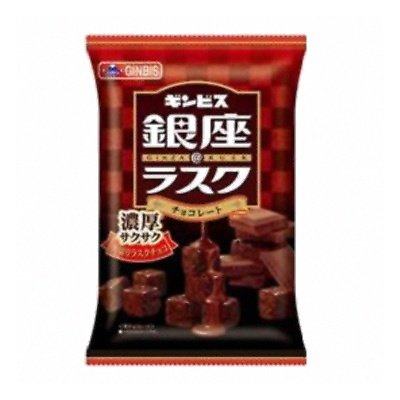
「銀座@ラスク」シリーズ
銀座@ラスクはとろける食感の新食感チョコラスクとして定期的に様々なフレーバーが発売されている。
銀座@ラスクのパッケージのタイトルにダイナフォントロマン鳳が採用
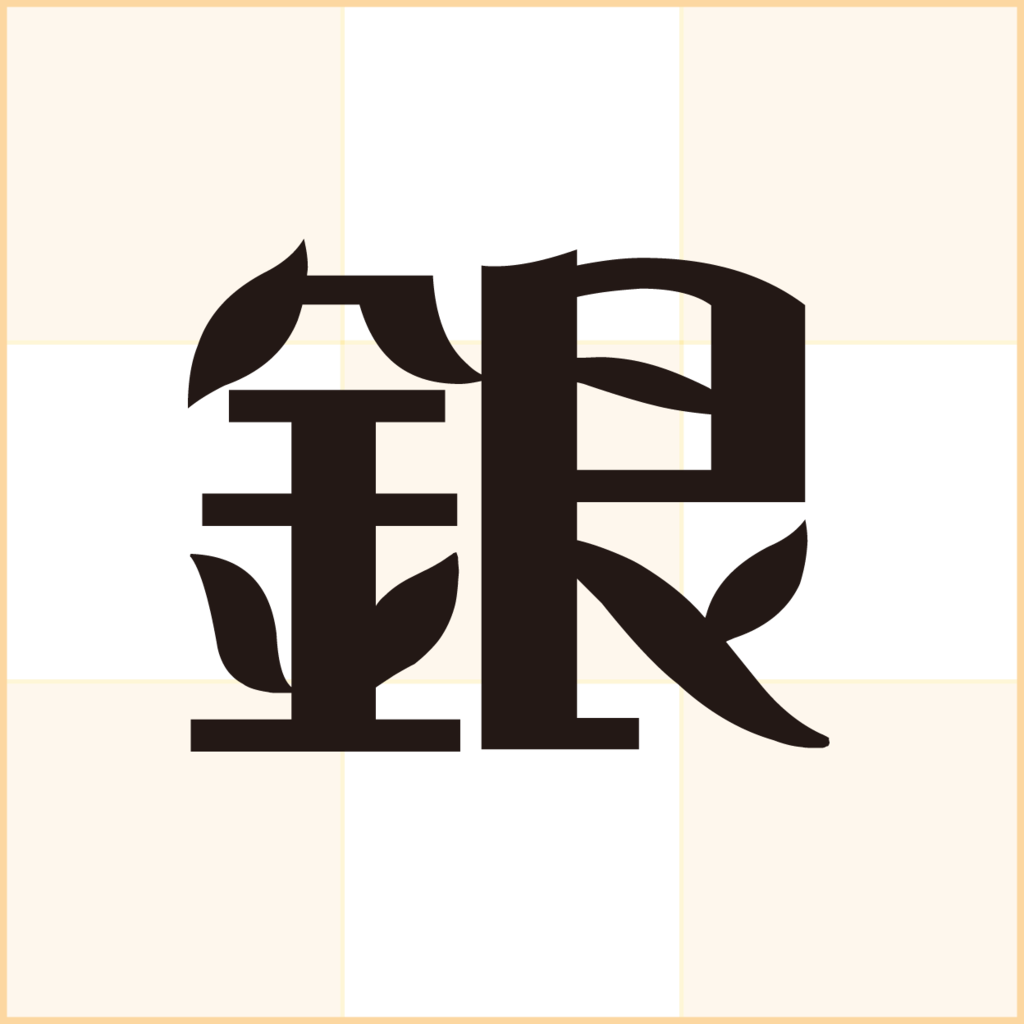
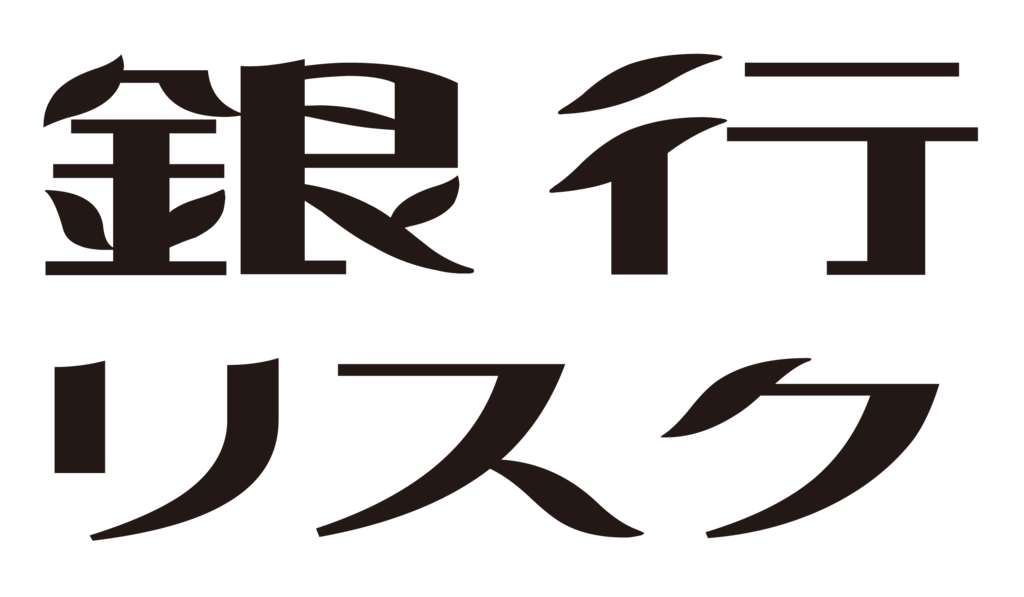
「アスパラガスビスケット」「たべっ子どうぶつ」でおなじみのギンビスが製造・販売する「銀座@ラスク」シリーズに「ダイナフォント ロマン鳳」が採用されている。
ロマン鳳
昭和2年に発行の『演芸と映画』を元ネタに、浮世絵的なスタイルを文字印象に応用した書体。葉っぱの形状を、右はらい・左はらいなどのストロークに取り入れている。また部分的に半円狐を組み合わせることで、ややフラットな字形で穏やかさをイメージさせた。